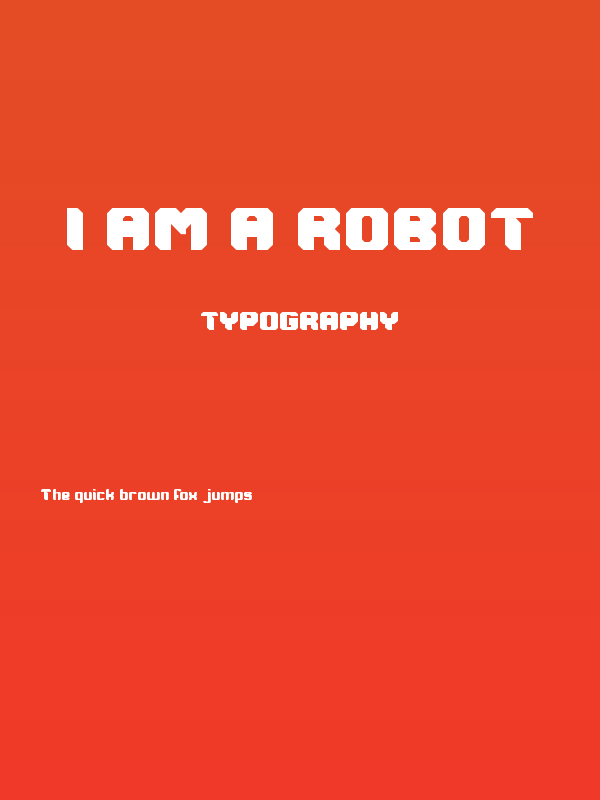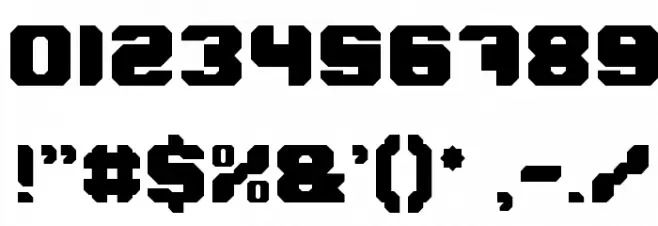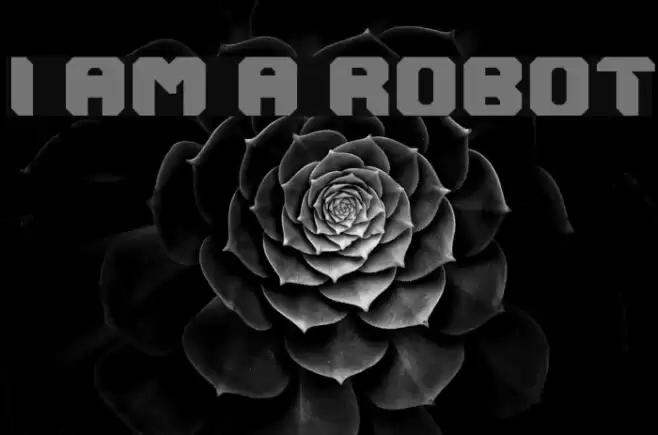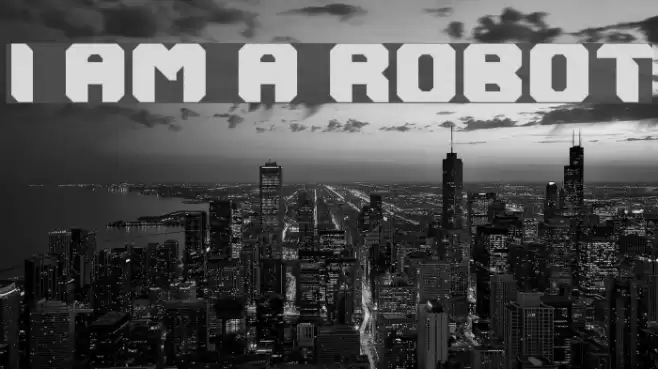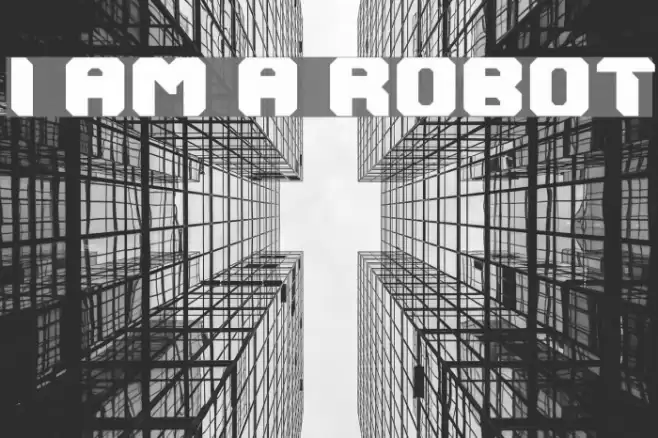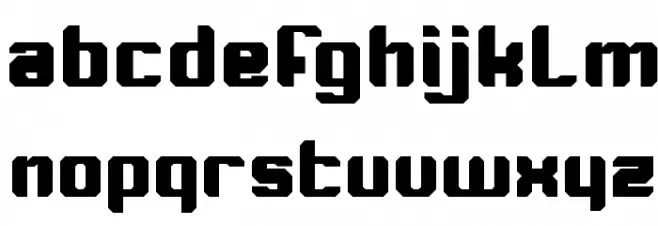
I AM A ROBOT Font
✎ Futuristic
| श्रेणियाँ | Futuristic |
| समग्र शैली | Futuristic, Industrial |
| उपयोग का मामला | Headlines, Logos, Posters |
| सुझाए गए प्रोजेक्ट | Ideal for technology branding, sci-fi movie posters, video game titles, and futuristic-themed designs. |